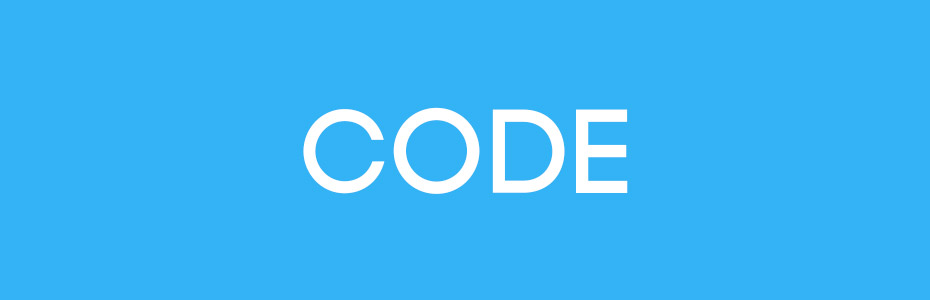
10 Free Fonts hoạt động tốt trên bất kỳ Video
Bạn đã bao giờ nhận thấy rằng có khoảng 1,5 triệu lựa chọn phông chữ trong thị trường? Không sao đâu. Có thực sự là một cái gì đó cho mọi nhu cầu. Và có rất nhiều các nhà sản xuất phông chữ lớn tạo phông chữ đẹp.
Nhưng, chúng ta hãy đối mặt với nó, cho các nhà sản xuất video trung bình trên mạng, nó có thể là một chút áp đảo đôi khi. Bạn có thể tìm thấy thời gian mà bạn thực sự cần phải săn lùng chỉ font chữ cho một phong cách nhất định của đồ họa, nhưng thường xuyên hơn không, bạn chỉ cần một nồi đồng cối đá rắn rằng sẽ xem xét tốt và hoàn thành công việc mà không cần phải suy nghĩ quá khó về nó.
Đồng thời, bạn không muốn chỉ cần sử dụng font chữ giống nhau cho mỗi dự án video duy nhất một trong hai. Đó là lý do tại sao chúng tôi đã tập hợp danh sách này là 10 (một số chỉ cá nhân) phông chữ lớn miễn phí sẽ làm việc tuyệt vời trong bất kỳ dự án video.
Bebas Neue
Bebas Neue là một phông chữ đặc đẹp với chữ rõ ràng. Tạo bởi Pháp Gõ vào năm 2010 như là một bản cập nhật cho Bebas font chữ ban đầu từ năm 2005 , Bebas Neue đã được sử dụng trong vô số mảnh in và video.
Code
Tìm kiếm một cái gì đó tốt đẹp và tròn với vòng tròn " O " hoàn hảo ? Nhìn không có thêm hơn Mã . Mã được tạo ra bởi các folks tài năng tại Fontfabric và là một sự kết hợp của những đường thẳng siêu và cạnh siêu tròn , làm cho nó siêu dễ dàng trên mắt . Mã đi kèm trong một loạt các trọng lượng có thể được mua , nhưng các biến thể nhẹ và Bold được miễn phí. Mã cũng là một phông chữ tất cả mũ , vì vậy nó rất lớn đối với nhiều người sử dụng , nhưng có lẽ không phải tất cả .
Caviar Dreams
How about a little retro appeal for your next video? Caviar Dreams adds a little bit of Art Deco pizazz to a lovely rounded font.
Nymphont created this very easy to read font with a slight feminine edge back in 2009, and made it free for both personal and commercial use. Some of the unique letter forms like the tilted lowercase “e” add a bit of fun without taking away from the overall legibility.
Caviar Dreams will work well in loads of video settings and it is a full font set with uppercase, lowercase, numbers, and several special characters.
Big Noodle Titling
Big Noodle is another great font for titling and short form text. It’s a condensed font with bold forms and a slightly futuristic edge. The sharp corners give this one a little attitude.
Chunk Five
I say slab, you say serif…..slab…..serif. Chunk Five is one thick font with some serious slabs. This font carries weight, and is perfect for really getting noticed.
Chunk Five was created by The League Of Moveable Type who have a number of really great fonts for free use. With this set, they aimed to recreate the feel of woodcuts and old newspaper headlines.
Comfortaa
Where Code gave us perfectly rounded “O’s”, Comfortaa gives us rounded everything. Comfortaa is the epitome of a rounded font. Smooth on all sides.
This font set created by Johan Aakerlund, will fit perfectly into any modern look or even futuristic designs. The generous letter spacing and balanced round shapes also make it super easy to read. Comfortaa will work in just about any setting that you want to try it, and it’s free for both personal and commercial uses.
Couture
Couture is another really well balanced uppercase font set based around the iconic “C” letter form used in the CoCo Channel logo.
The font is bold without getting too heavy. The letters carry a masculine edge, but with some round touches and personality given to letters like Q and K.
This set is another really solid choice for titles, lower thirds, and anything that calls for attention. Creator Charles Babb has put Couture out for free for personal use.
Sansumi
Want something a little out of the ordinary, but still useful for many settings? Take a look at Sansumi.
Sansumi is a thin font with some really interesting letterforms. It’s got a slightly retro tilt, and almost a hand drawn quality while maintaining perfect balance and edges. The font created by Manfred Klein, comes in 4 weights from ultralight to bold, although even the bold is fairly thin.